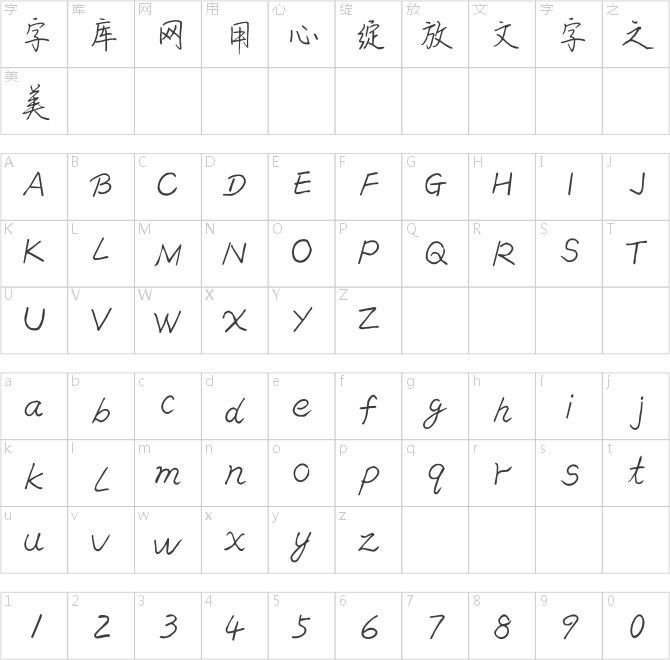
騰祥妮妮手跡簡 詳情頁
字體名稱: 騰祥妮妮手跡簡
騰祥妮妮手跡簡
此款字為騰祥妮妮手跡。書寫連貫輕松自如,平實無華的風(fēng)格透顯出質(zhì)樸與生機,充滿活力。適用于正文更體現(xiàn)出親切、自然之感,具實用性。
騰祥妮妮手跡簡字體TTNiNiJ字庫是一款讓人賞心悅目、百看不厭的中文字體,適合各類廣告和產(chǎn)品包裝設(shè)計應(yīng)用,字體大小9.63MB,格式為ttf字體,上傳用戶是rose,作者/版權(quán)方為騰祥字庫